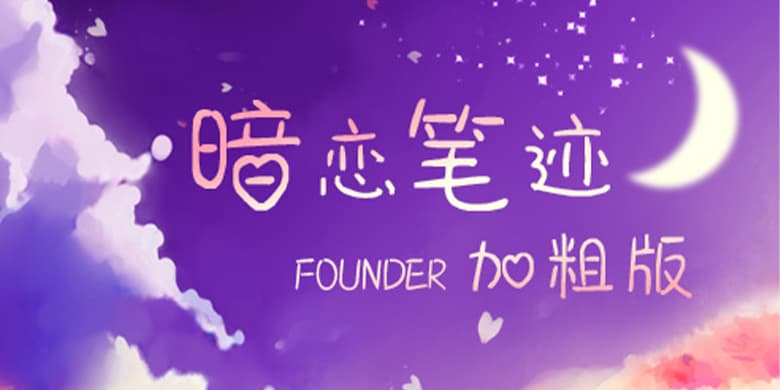
品牌:方正手迹设计师:王航发行时间:2020字库编码:大陆简体(GB2312-80)分类:创意书写字体属性:精品字
宽松的中宫,简洁的笔画,轻松大方的字形,圆润的转角处理,温婉迷人,加上化“口”为爱心,简直是少女气息满满,阅读起来有心动的感觉。适用于少年儿童类的书刊、品牌广告和产品包装设计,以及社交网络的个性化用字。